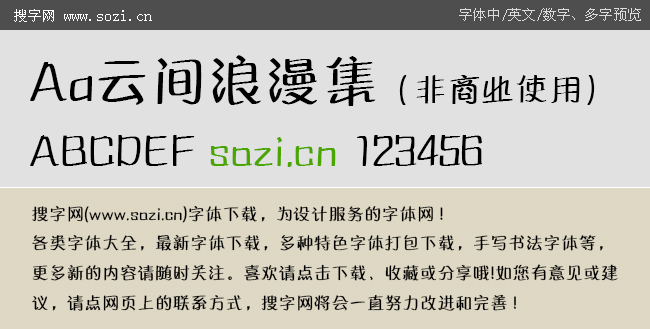
Aa云間浪漫集
搜字網(wǎng)給大家提供一款Aa云間浪漫集(非商業(yè)使用)中文字體下載,Aa云間浪漫集是一款藝術字體,該字體筆畫自然隨性,個別筆劃帶有波浪形狀的變形效果,字體充滿浪漫氣息,視覺效果非常棒。適合應用于海報設計、包裝設計、網(wǎng)頁設計等應用(此字體為個人非商用版,商用可以聯(lián)系QQ:1006760504)。